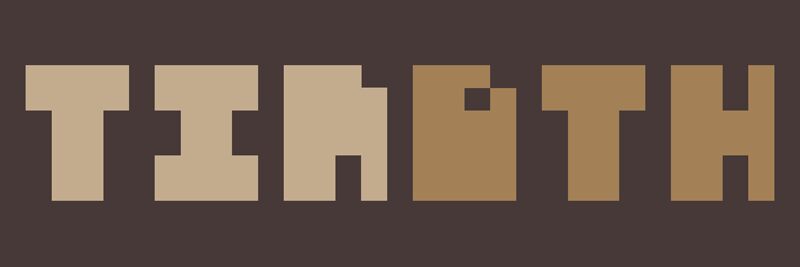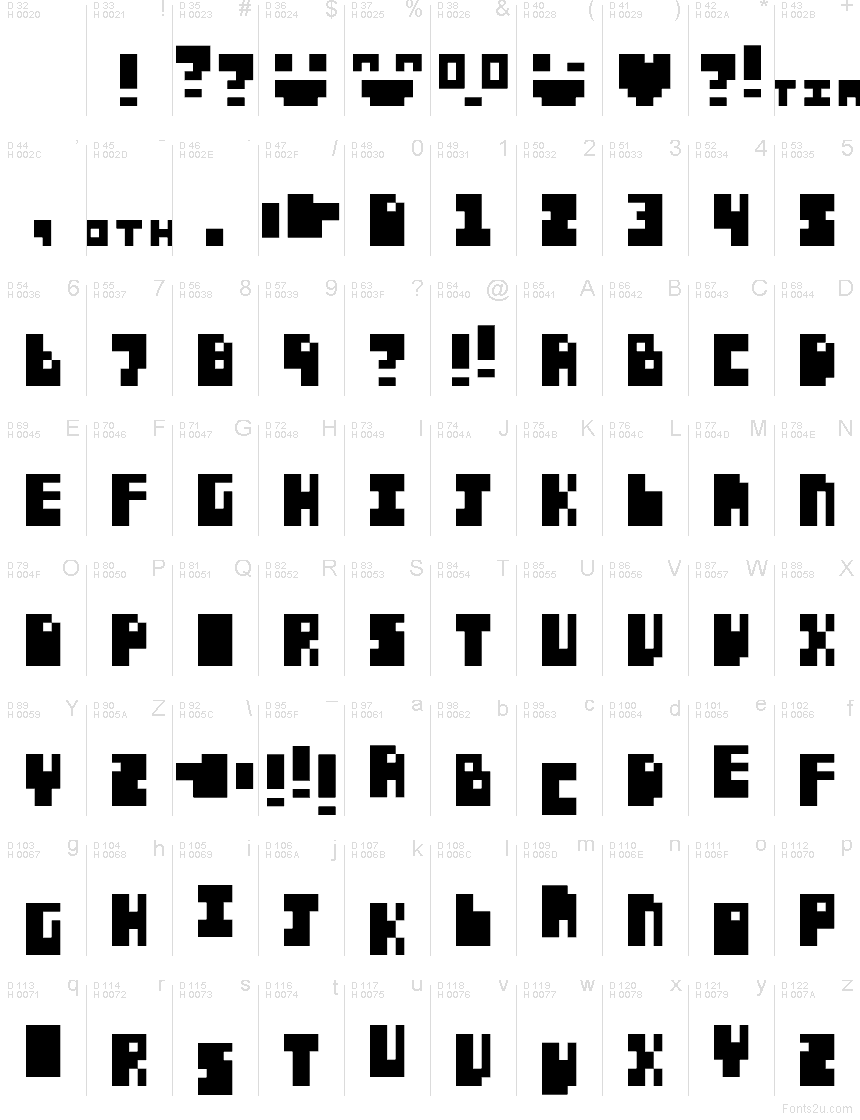
Oth Logo od Potionpro je bezplatné pixelové písmo typu display, složené z masivních obdélníkových tahů a ostrých, pravoúhlých řezů. Jeho kompaktní písmena mají neotesanost arkádové obrazovky a husté tvary v nich přerušují malé čtvercové výřezy.
Ve hrách a digitální grafice se bloková konstrukce hodí pro úvodní obrazovky, prvky rozhraní a propagační materiály se záměrně nízkým rozlišením. Stejná strohá geometrie se uplatní na plakátech elektronické hudby a merchi pro technologicky zaměřené značky. Tyto čtvercové výřezy připomínají pixely a okna obrazovky, čímž mění nápisy v rozhraní nebo grafiku herního světa.